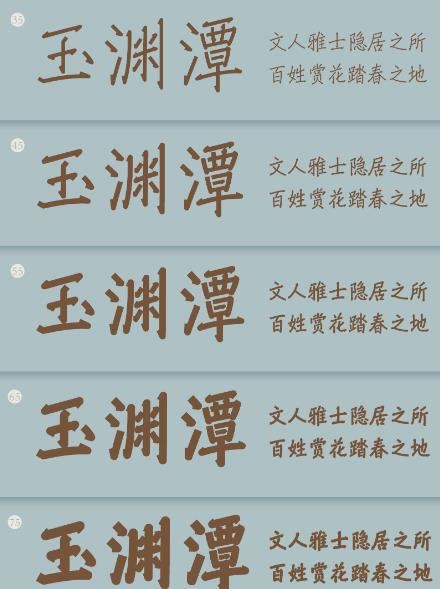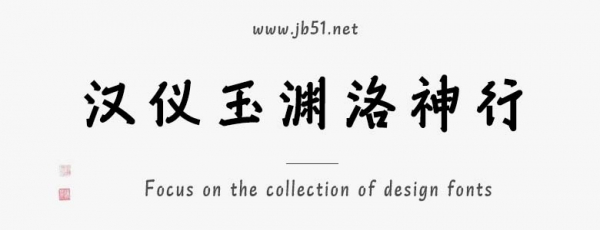
漢儀玉淵洛神行家族由漢儀字庫(kù)出品的藝術(shù)字體,字體簡(jiǎn)化書寫線條的粗細(xì)變化,等線筆畫清晰而簡(jiǎn)約,運(yùn)用幾何構(gòu)成,具有現(xiàn)代氣息,適合應(yīng)用于藝術(shù)設(shè)計(jì)、平面宣傳設(shè)計(jì)、網(wǎng)頁(yè)設(shè)計(jì),書法字帖等領(lǐng)域。有需要的朋友快來(lái)本站下載使用吧。
漢儀玉淵洛神行,取意趙孟頫行書《洛神賦》卷,行中兼楷,在字形結(jié)構(gòu)上尋求“竦輕軀以鶴立,若將飛而未翔”的意境,結(jié)合現(xiàn)代等線的筆畫設(shè)計(jì),保留行楷的流暢瀟灑。敘寫漢字書法的現(xiàn)代美學(xué),徐徐展開一卷中式浪漫,含蓄蘊(yùn)藉。
漢儀玉淵洛神行,適用于公園內(nèi)的文化藝術(shù)類展覽,兼有文人雅士之古韻和現(xiàn)代簡(jiǎn)約之審美,具有優(yōu)雅的書卷氣息。
字形挺拔如鶴立,略帶書寫的自然傾斜,呈現(xiàn)“若將飛而未翔”之勢(shì),具有優(yōu)雅的書卷氣質(zhì)。
簡(jiǎn)化書寫線條的粗細(xì)變化,等線筆畫清晰而簡(jiǎn)約,運(yùn)用幾何構(gòu)成,具有現(xiàn)代氣息。
在筆畫設(shè)計(jì)中運(yùn)用幾何構(gòu)成,方直的起收筆與圓形的轉(zhuǎn)折相互平衡。
漢儀玉淵洛神行家族包含 5 種字重,可以滿足不同視覺層級(jí)的排版需求,保證字體風(fēng)格一致的同時(shí)又有細(xì)膩的差異,和而不同:細(xì)款翩翩而行,纖韌輕盈;粗款徐徐流轉(zhuǎn),溫潤(rùn)厚重。
漢儀玉淵洛神行,具有連結(jié)古今的現(xiàn)代書卷氣息,適用于公園內(nèi)的文化藝術(shù)類展覽,體現(xiàn)公園的歷史文化底蘊(yùn)。
西文設(shè)計(jì)同樣將方直的起收筆與圓形的頓筆結(jié)合,線條婉轉(zhuǎn)流動(dòng),與中文設(shè)計(jì)相互呼應(yīng)。